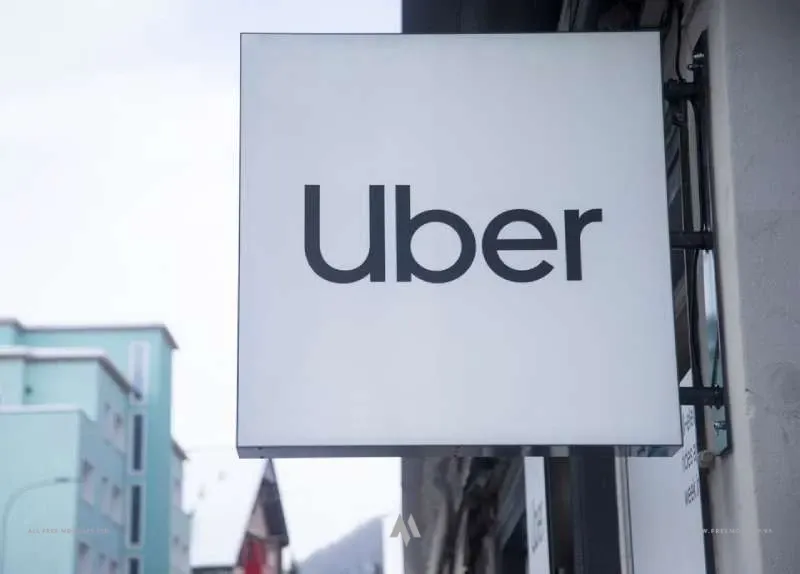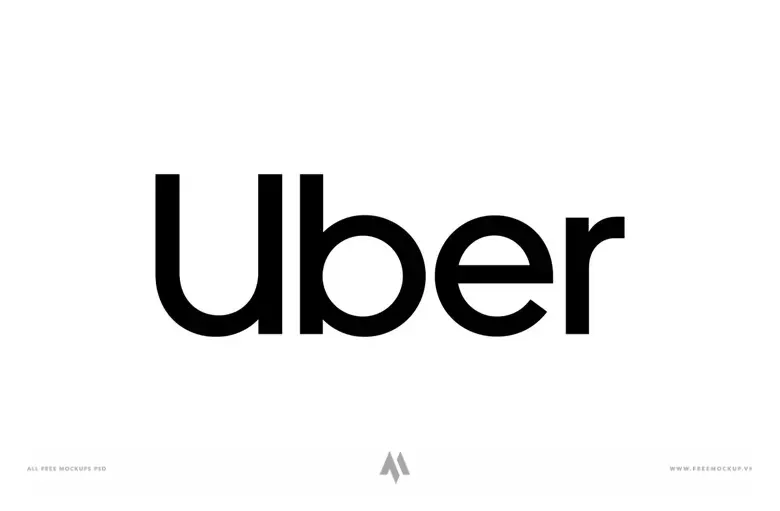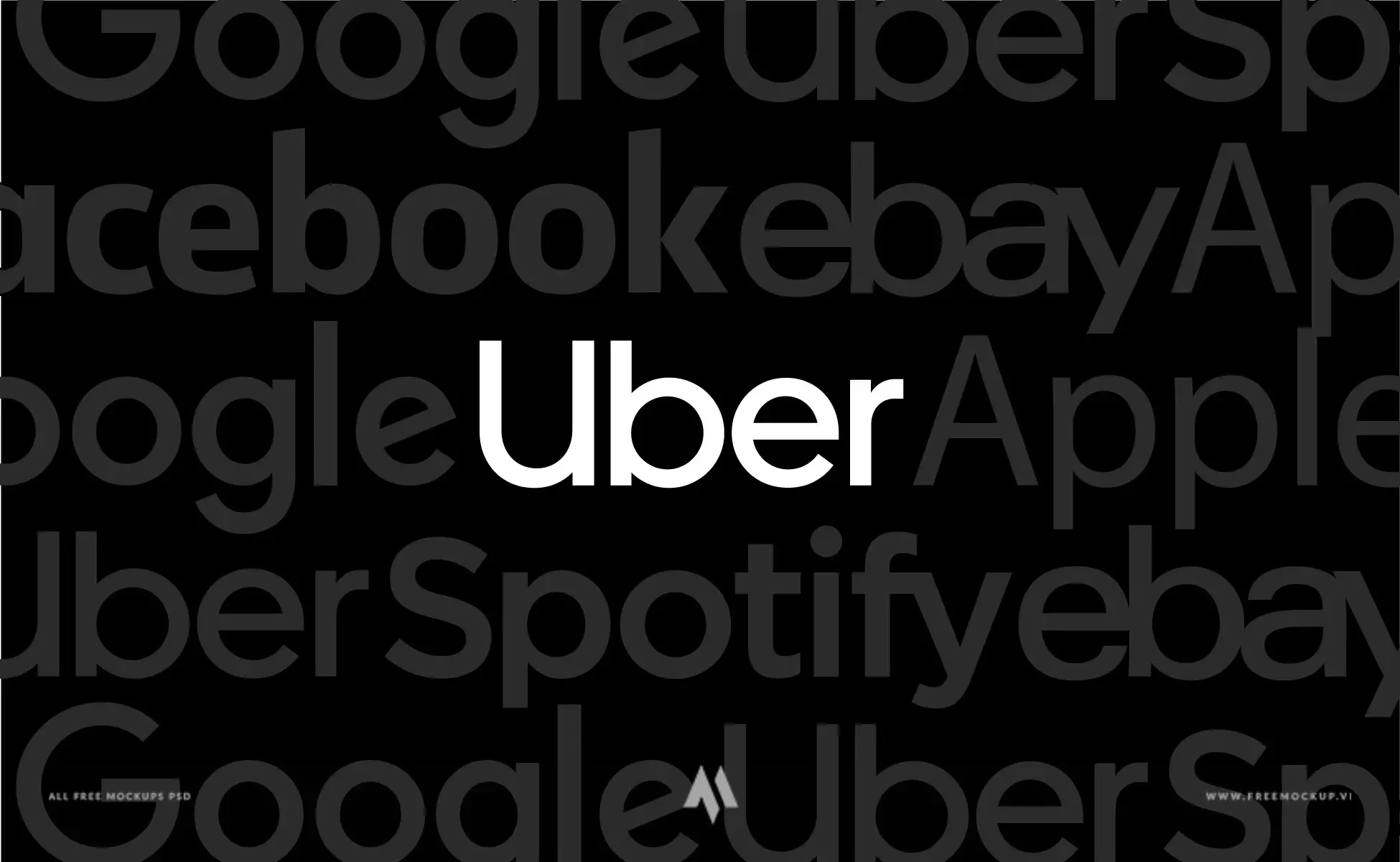
Font Uber Move Việt Hóa (Medium & Bold) là bộ phông chữ không chân (Geometric Sans-Serif) mang tính biểu tượng, được tối ưu hóa từ ngôn ngữ nhận diện thương hiệu toàn cầu của tập đoàn công nghệ Uber. Sở hữu cấu trúc hình học chuẩn mực, nét chữ vuông vức, tinh giản và đầy bản lĩnh, bộ font là lựa chọn hàng đầu cho các dự án thiết kế đòi hỏi tính chuyên nghiệp, hiện đại và chuẩn công nghệ.